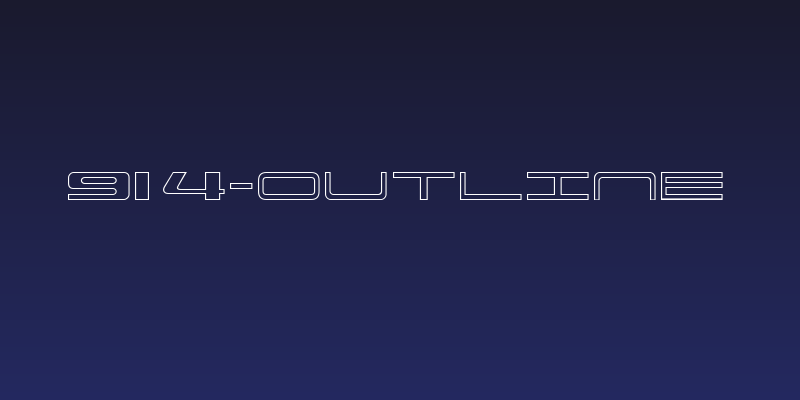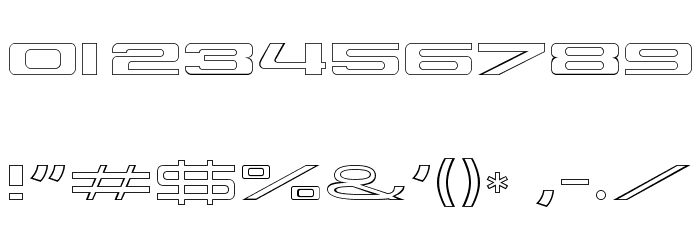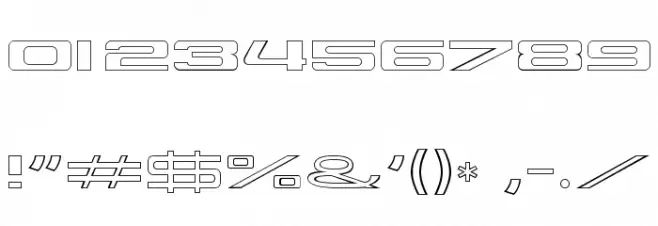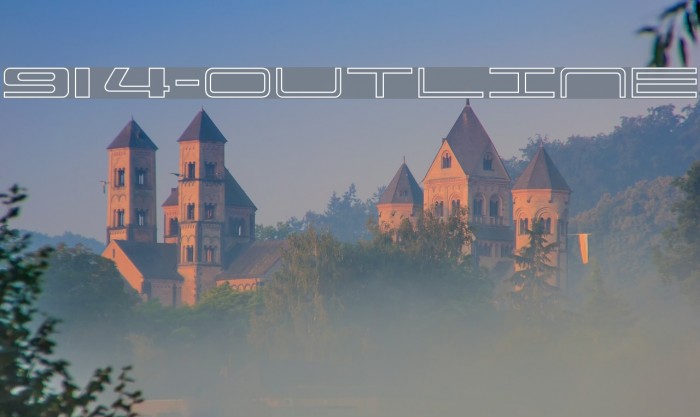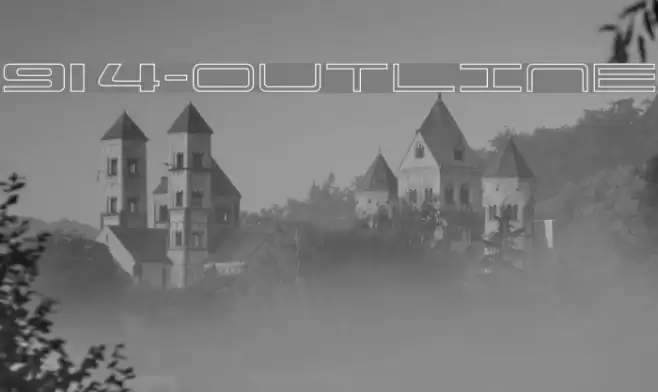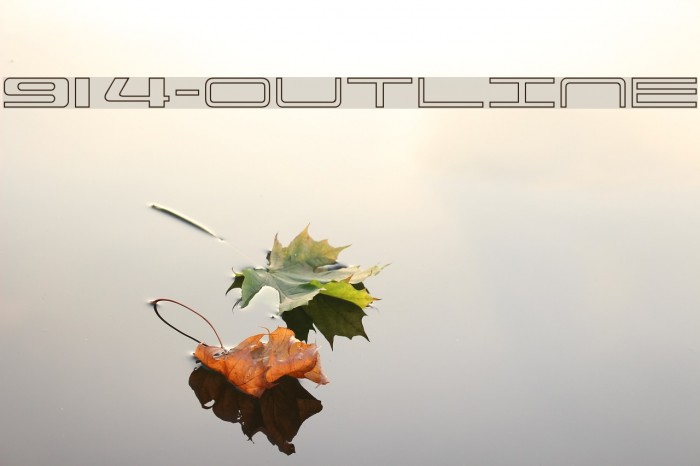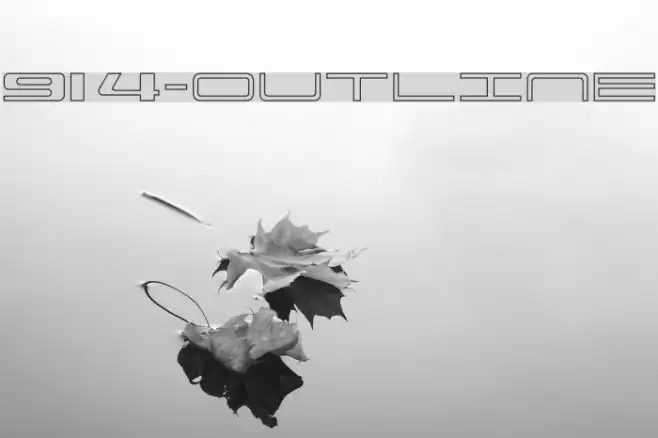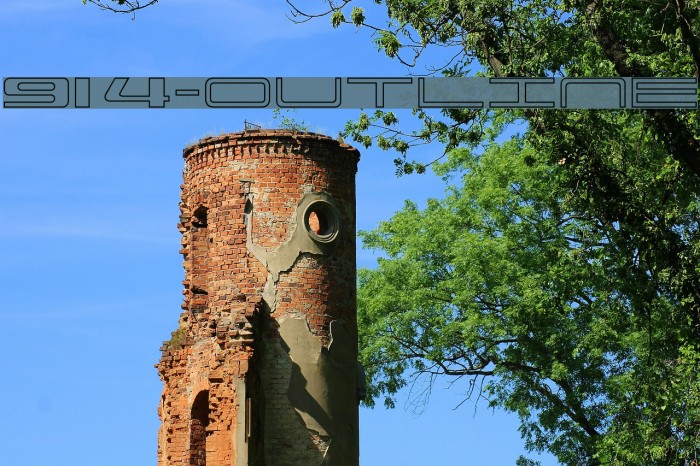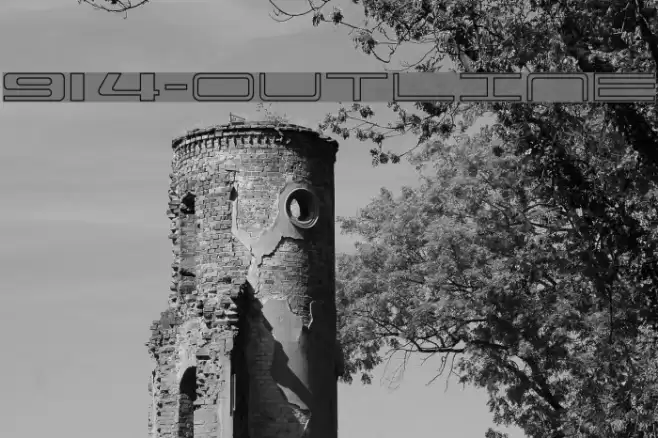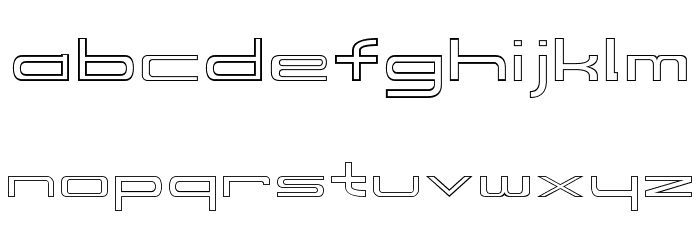
914-OUTLINE Font
| Kategorien | Outline |
| Anwendungsfall | Logos, Headlines, Posters |
| Vorgeschlagene Projekte | Ideal for tech-related branding, futuristic designs, digital art projects, and modern advertising campaigns. |